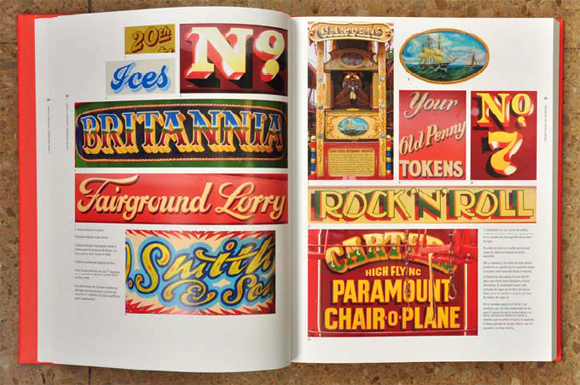
En unostiposduros tenemos muy claro que la tipografía es una parte esencial de la cultura popular y como tal su representación ha saltado del material impreso a todo tipo de soportes. Y de cómo se materializa la letra en estos soportes precisamente es de lo que trata el nuevo libro editado por Gustavo Gili.
Lettering de Andrew Haslam es un paseo didáctico por todas las formas y soluciones de producción de las letras partiendo desde las formas caligráficas dibujadas a mano y terminando por las letras animadas de los soportes digitales. Entre medias el autor nos muestra las letras tipográficas fundidas e impresas, las letras tridimensionales talladas y grabadas, letras tridimensionales moldeadas y fundidas y las letras en soporte textil.
Con esta cantidad de información no podemos menos que decir que este título es una enciclopedia de producción de la letra, con una estructura muy bien articulada, con unos textos claros y concisos y con una cantidad impresionante de imágenes que ilustran cada proceso de una forma autoexplicativa.
A nosotros nos parece un libro básico para todos los que tenemos que ver con la tipografía: diseñadores, creativos multimedia, artesanos y artistas plásticos encontrarán en sus páginas soporte e inspiración para sus proyectos así como procesos detallados paso a paso.